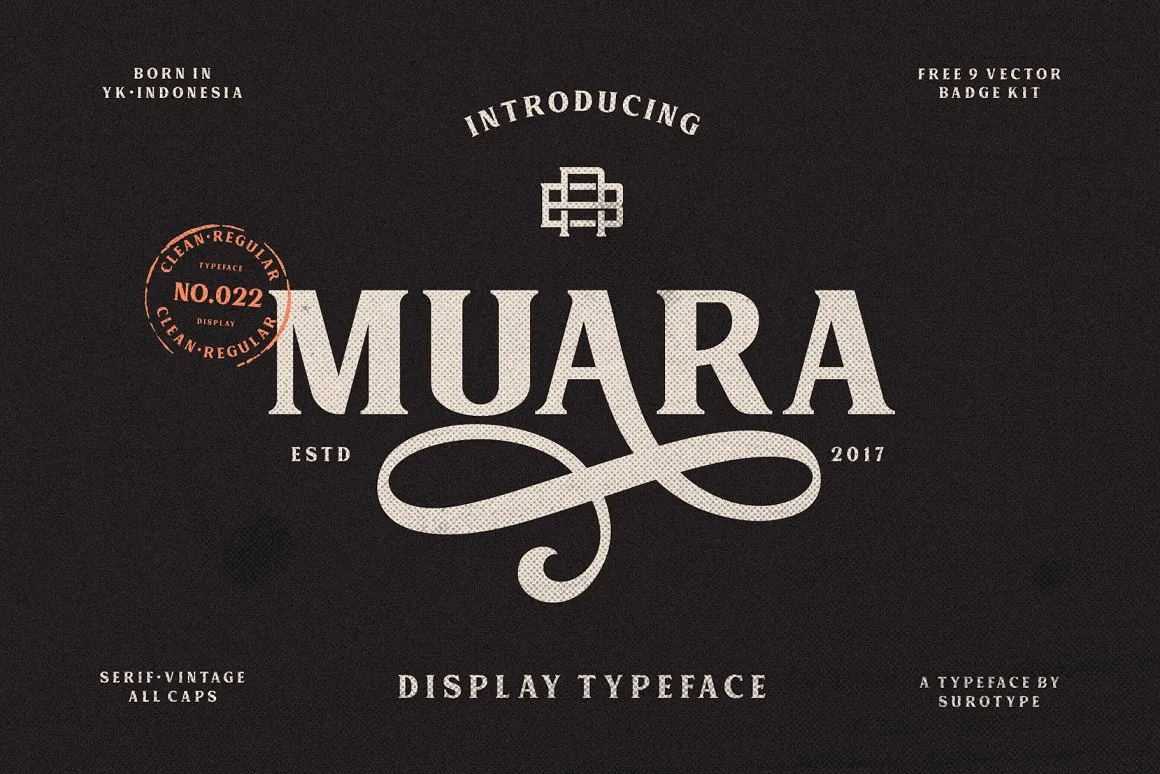
Na evolução constante dos estilos tipográficos, introduzimos uma nova opção para 2018 com a MUARA Typeface. Esta é uma tipografia serif de estilo clássico ideal para design gráfico variado, desde revistas e livros até embalagens e identidades corporativas. A criação de Adil Budianto destaca-se pelo seu sabor inconfundível, adequada a múltiplas aplicações em projetos criativos. Uma característica marcante é sua aparência clássica que combina perfeitamente com estilos tradicionais e sofisticados. A MUARA oferece uma vasta gama de opções para seus usuários, incluindo recursos OpenType avançados e caracteres alternativos disponíveis apenas na versão Full. Para acessar essas funcionalidades, no entanto, é necessário adquirir a versão completa do produto. Esta tipografia não só adicionará um toque elegante às suas criações, mas também proporcionará uma conexão com o passado através de seu design clássico e sofisticado. Compreender a relevância da MUARA no panorama dos estilos tipográficos pode transformar seus trabalhos em projetos de design em algo realmente único e diferenciado. Agradeçamos por escolher adquirir nossa fonte, uma verdadeira dádiva para qualquer designer gráfico.